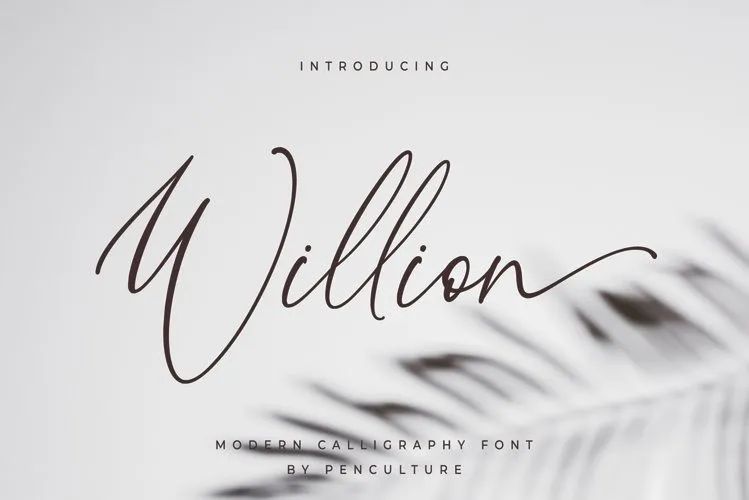
A Willion é uma fonte script criada pela Pen Culture que apresenta diversas estilos alternativos, ligaturas e letras multilíngues para atender todos os seus projetos. Com um design encantador, a Willion é perfeita para qualquer projeto de branding ou ilustração de produto, bem como para adicionar um estilo elegante aos fundos de imagem de qualquer tipo de arte digital. A fonte será uma ótima escolha para designers que desejam dar um toque sofisticado e único a seus projetos, seja em design de produtos, embalagens ou até mesmo textura de imagem background.